Voor wie net als J.C. Bloem soms wat droefgeestig is, heb ik een troostrijke (?) mededeling: hij had ook opgewekte momenten. Al waren die soms maar vier regels lang. Zijn gedicht „Voorjaar” gebruikte ik voor onze lentewens.
De zon brak door de barre voorjaarslucht.
Plotseling kantelde er een vogelvlucht.
Op de aarde smolt de dungezaaide sneeuw.
Hart, gij zijt vrij; gij waart om niets beducht.
Het kwatrijn van Bloem heeft wel iets van een haiku, al is de vorm anders. Dat ik net de „Japanse” bindwijze had geleerd, kwam goed uit.
Bij deze manier van boekbinden wordt oorspronkelijk vrij dun papier gebruikt. Dat wordt aan één zijde bedrukt en dan dubbelgeslagen, met de bedrukte kant naar buiten. De „losse” uiteinden van de vellen worden aan elkaar genaaid en komen dus aan de kant van de rug. Vaak gebruik ik wat zwaarder papier voor mijn kaartjes, maar dat kon hier dus écht niet. Voor een mooie afdruk probeerde ik nog 120 grams fotopapier, maar dat was te stug voor zo’n klein boekje.
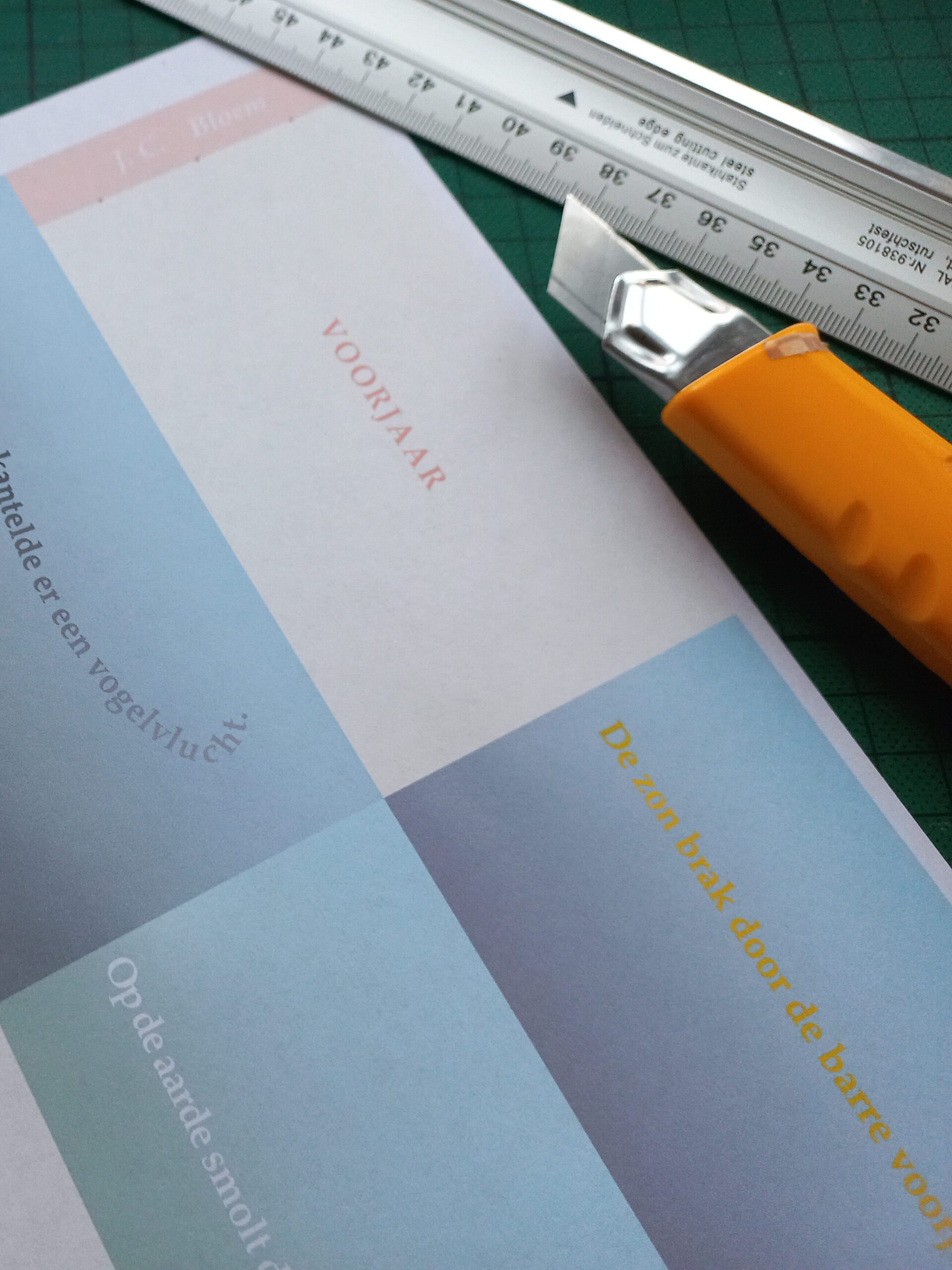
Aan de andere kant, ik gebruikte hier geen felle kleuren dus fotopapier was niet per se nodig, en het 75 grams flutpapier van de HEMA bleek wonderwel geschikt. Verder bleef het boekje ook heel eenvoudig, zonder harde band. Voor het binden viste ik groen borduurgaren uit één van Corries voorraaddozen.
Op de voorpagina drukte ik drie rode stipjes mee, om aan te geven waar de gaatjes voor het garen moesten komen. Ik had een kartonnen mal gemaakt om de velletjes gelijk te leggen. De gaatjes prikte ik vóór met mijn boekbinderspriem.
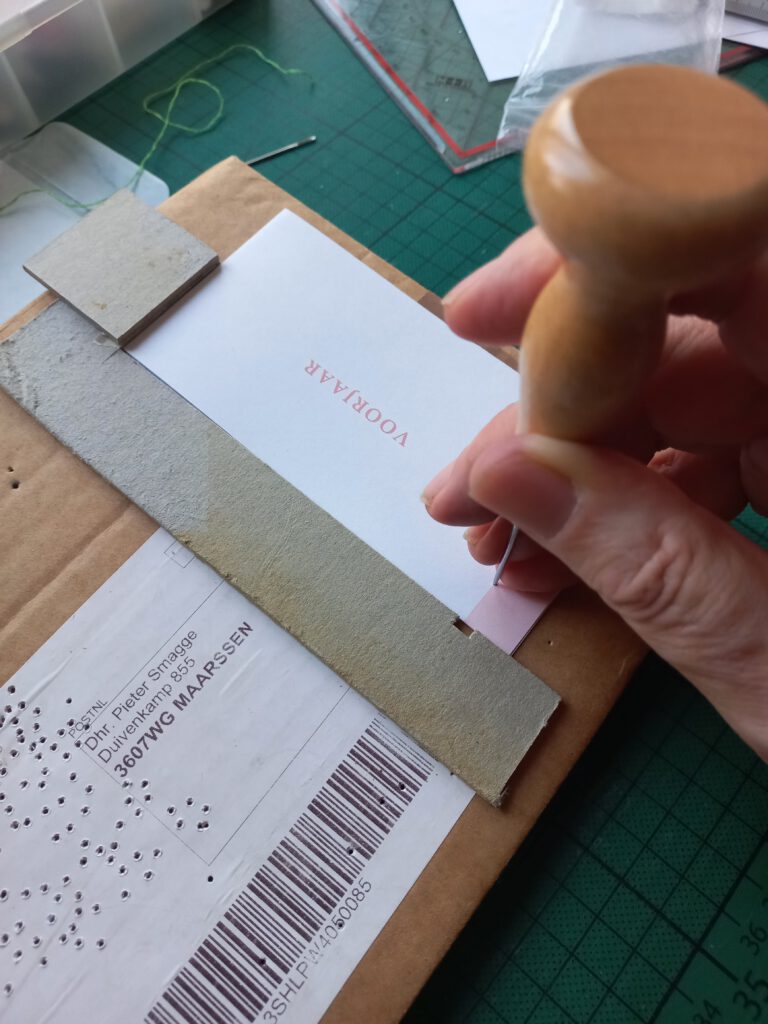
Met die voorgeprikte gaatjes was het boekje makkelijker te naaien. De mal kwam nu ook weer van pas, evenals een gewicht om het schuiven tegen te gaan. En ja, je ziet hieronder een krukje op mijn bureau staan; zo had ik een prettige werkhoogte voor al die boekjes.
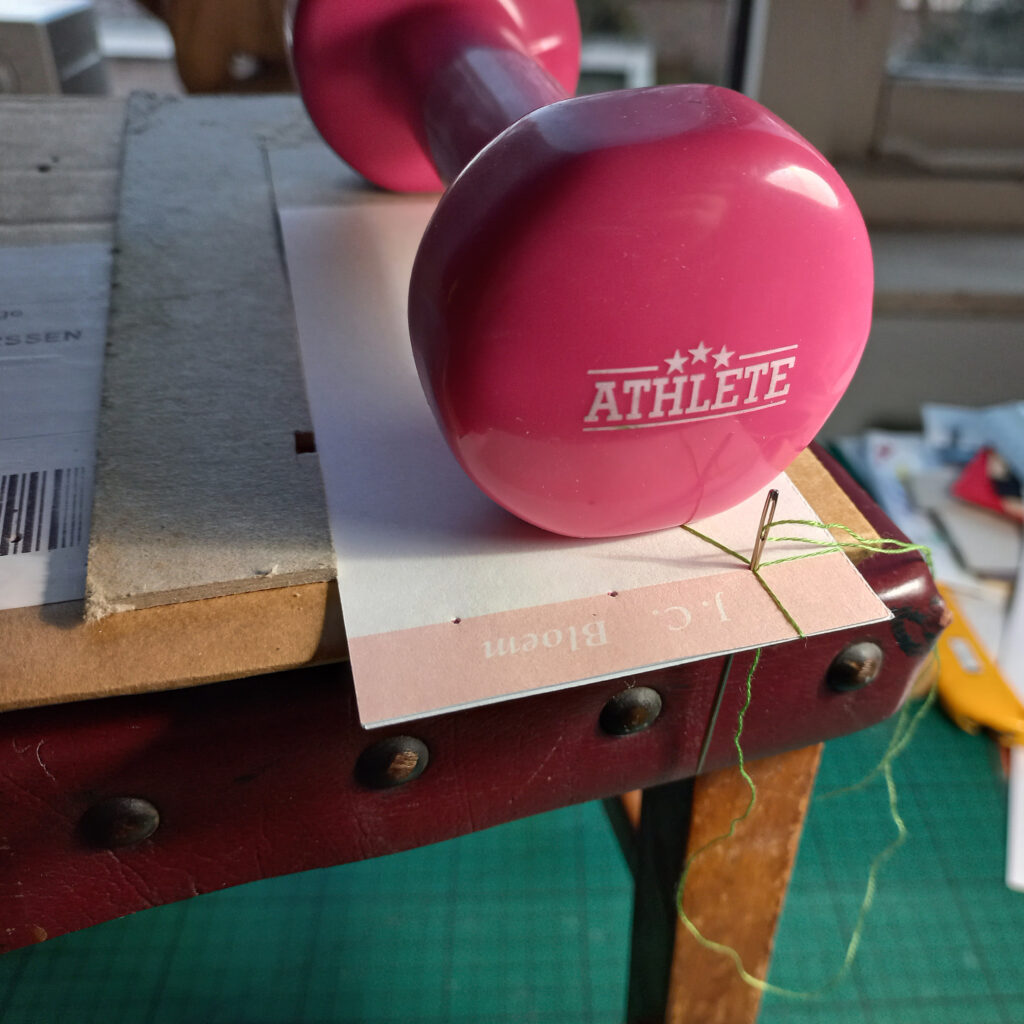
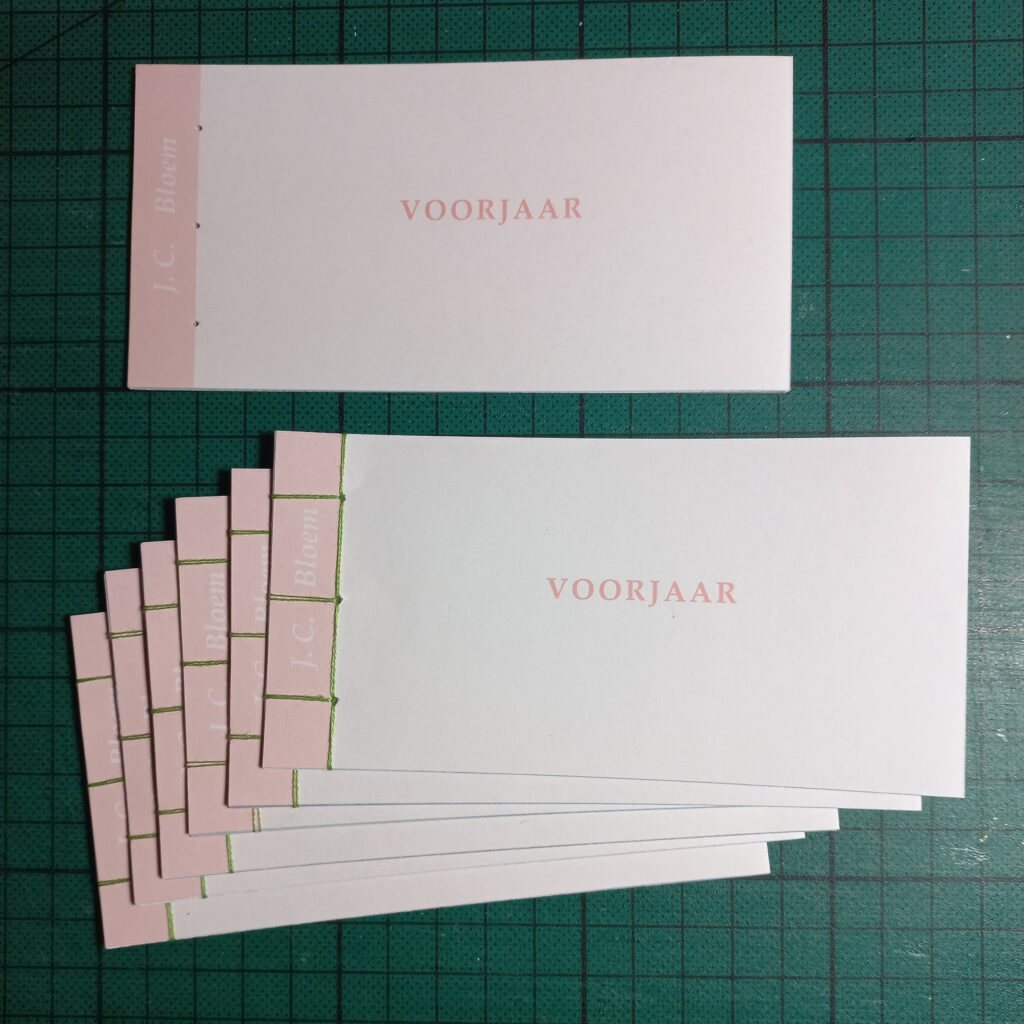
Achteraf bleek dat ik wat ál te zachte kleuren had gebruikt: één van mijn zwagers vond de eerste regel / tweede bladzijde, in verlopende tinten geel op lichtblauw, nauwelijks te lezen. Andere eigenaars van oudere ogen klaagden niet, maar ze zullen ook wel moeite hebben gehad …